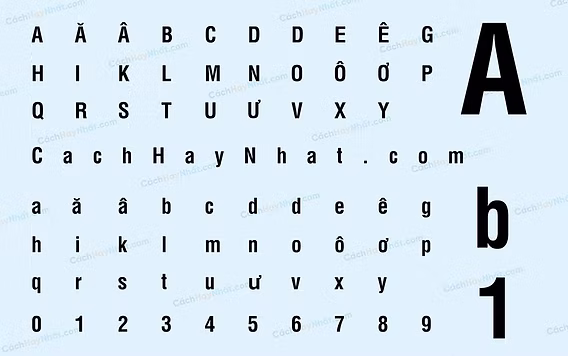
Nhu cầu tải font VNI Helve Condense vẫn rất phổ biến, đặc biệt với những ai thường xuyên làm việc với bản vẽ CAD cũ. Trong bài viết này, Xưởng In Viva chia sẻ bộ download font VNI Helve Condense để bạn sử dụng ổn định hơn khi mở và xử lý file kỹ thuật.
VNI Helve Condense là kiểu chữ có cấu trúc gọn, thẳng, dễ đọc và chiếm ít không gian chiều ngang hơn so với nhiều font thông thường. Đây là lý do font này được dùng khá nhiều trong môi trường CAD để đảm bảo nội dung rõ ràng. Dưới đây là một số thông tin cơ bản khi tải font VNI Helve Condense:
| Tên font | VNI Helve Condense |
| Kiểu chữ | Sans-serif |
| Bảng mã | VNI |
| Ứng dụng | Bản vẽ AutoCAD |
Font VNI Helve Condense là gì?
VNI Helve Condense là một font chữ thường được dùng trong môi trường bản vẽ kỹ thuật, đặc biệt là các file AutoCAD cũ hoặc các bản vẽ được tạo theo hệ font VNI. Font này có đặc điểm là chiều ngang chữ hẹp hơn, nét gọn và rõ, nhờ đó phù hợp với những vùng ghi chú nhỏ nhưng yêu cầu hiển thị chính xác.
Khi tải font VNI Helve Condense cho AutoCAD, mục tiêu chính không phải để tạo hiệu ứng thẩm mỹ như trong thiết kế đồ họa, mà là để đảm bảo bản vẽ hiển thị đúng như file gốc, giữ nguyên các ghi chú, kích thước và thông tin quan trọng.
Dưới đây là những ưu điểm nổi bật khiến nhiều người tìm link tải font VNI Helve Condense khi xử lý file CAD:
- Chữ gọn gàng: kiểu chữ condense giúp tiết kiệm diện tích ngang, rất phù hợp với vùng ghi chú nhỏ trong bản vẽ.
- Dễ đọc: dù dùng ở kích thước nhỏ, chữ vẫn giữ được độ rõ cần thiết để theo dõi thông tin kỹ thuật.
- Phù hợp với AutoCAD: font này xuất hiện trong nhiều bản vẽ cũ nên có tính thực dụng cao khi mở và chỉnh sửa file.
- Tiết kiệm không gian trình bày: đây là ưu điểm rất quan trọng trong môi trường bản vẽ, nơi việc bố trí chữ luôn cần tối ưu diện tích.
- Phổ biến trong hồ sơ kỹ thuật cũ: nhờ được sử dụng từ lâu, font này giúp người dùng dễ khôi phục và đọc lại các file lưu trữ.
Chính nhờ những đặc điểm trên mà tải font chữ VNI Helve Condense vẫn là nhu cầu quen thuộc trong giới kỹ thuật và xây dựng.
Ứng dụng của font VNI Helve Condense
VNI Helve Condense không phải là font dùng phổ biến trong các thiết kế truyền thông hiện đại, nhưng trong môi trường kỹ thuật thì đây lại là một font rất thực tế. Giá trị của font không nằm ở tính sáng tạo thị giác mà nằm ở khả năng hiển thị ổn định và phù hợp với hệ thống bản vẽ cũ.
Một số ứng dụng phổ biến khi tải font VNI Helve Condense autocad gồm:
- Bản vẽ kiến trúc.
- Bản vẽ cơ khí.
- Bản vẽ xây dựng.
- Tài liệu kỹ thuật có phần chú thích bằng CAD.
- File AutoCAD cũ cần mở lại để chỉnh sửa.
- Hồ sơ thiết kế công trình và bản vẽ triển khai.
Nhờ đó, tải font VNI Helve Condense cho AutoCAD giúp người dùng đọc bản vẽ chính xác hơn, tránh việc phải đoán nội dung hoặc chỉnh sửa lại toàn bộ text chỉ vì lỗi font.
- Font thiếu bảng mã: chữ tiếng Việt hiển thị sai hoặc mất dấu nếu không đúng font VNI.
- File font bị lỗi: tải từ nguồn không ổn định khiến font không cài được hoặc hoạt động không đầy đủ.
Để hạn chế các lỗi này, bạn nên chọn nguồn tải font VNI Helve Condense cho AutoCAD đáng tin cậy và cài đủ cả các file cần thiết thay vì chỉ lấy một file riêng lẻ.
03 lưu ý khi sử dụng font VNI Helve Condense
Dù đây là font khá quen thuộc trong bản vẽ kỹ thuật, người dùng vẫn nên lưu ý một số điểm quan trọng để tránh lỗi hiển thị về sau. Điều này đặc biệt cần thiết nếu bạn thường xuyên làm việc trên nhiều máy khác nhau hoặc phải gửi file cho đối tác, nhà thầu và đồng nghiệp.
Khi tải font VNI Helve Condense và sử dụng cho CAD, bạn nên lưu ý:
- Cài đúng thư mục font của AutoCAD: đây là bước quan trọng để phần mềm nhận diện font đúng cách.
- Kiểm tra trước khi mở file quan trọng: nên thử font trên một bản vẽ mẫu để đảm bảo text hiển thị đúng.
- Giữ bản sao font để dùng lâu dài: nhiều bản vẽ cũ cần đúng bộ font đi kèm, nên bạn nên lưu lại để tránh mất thời gian tìm lại sau này.
Tải font VNI Helve Condense là giải pháp cần thiết nếu bạn thường xuyên làm việc với bản vẽ AutoCAD cũ và muốn đảm bảo toàn bộ nội dung hiển thị đúng như file gốc. Khi download font VNI Helve Condense đầy đủ, việc mở file, đọc chú thích và chỉnh sửa bản vẽ sẽ thuận tiện và chính xác hơn.